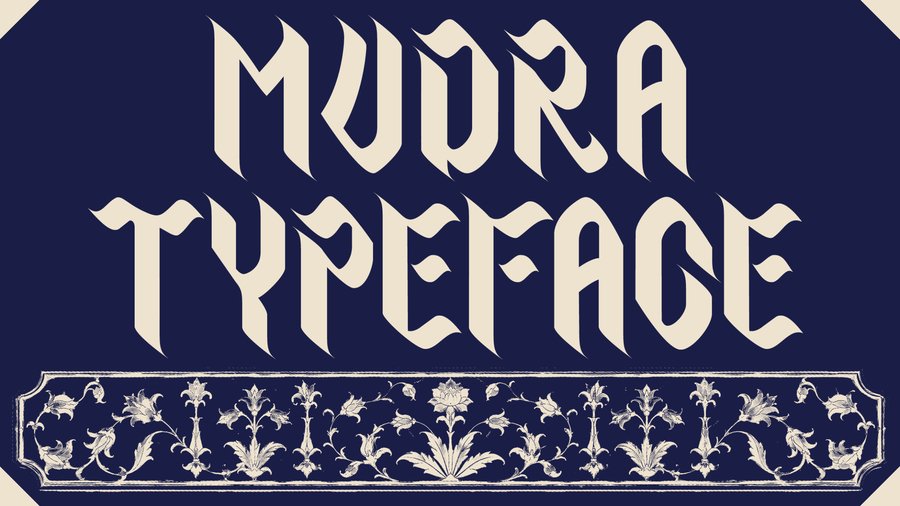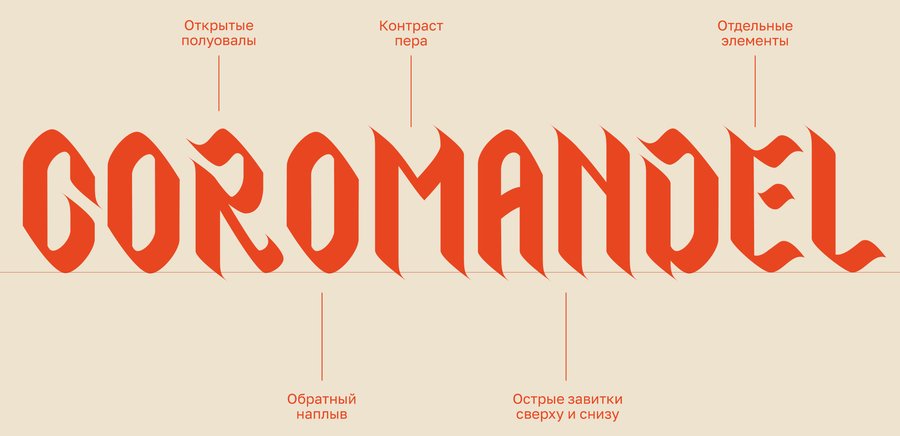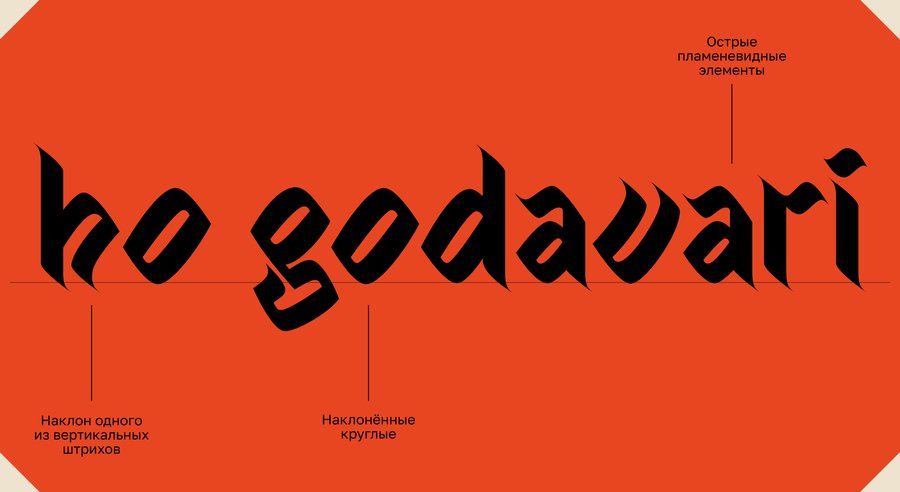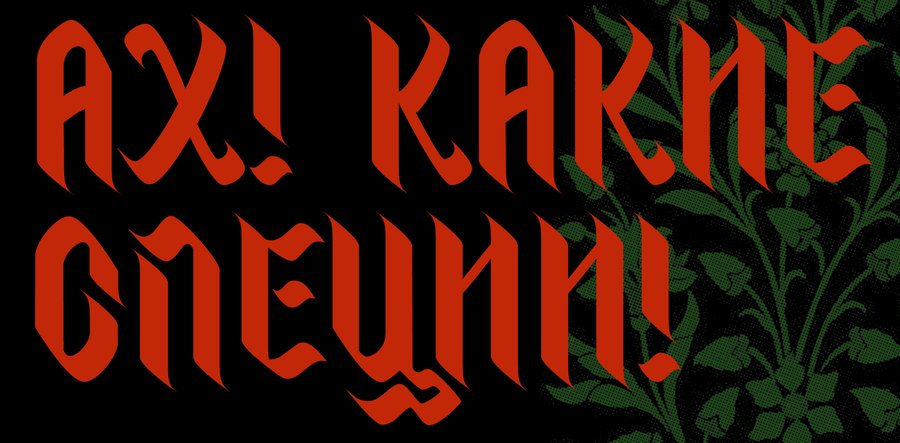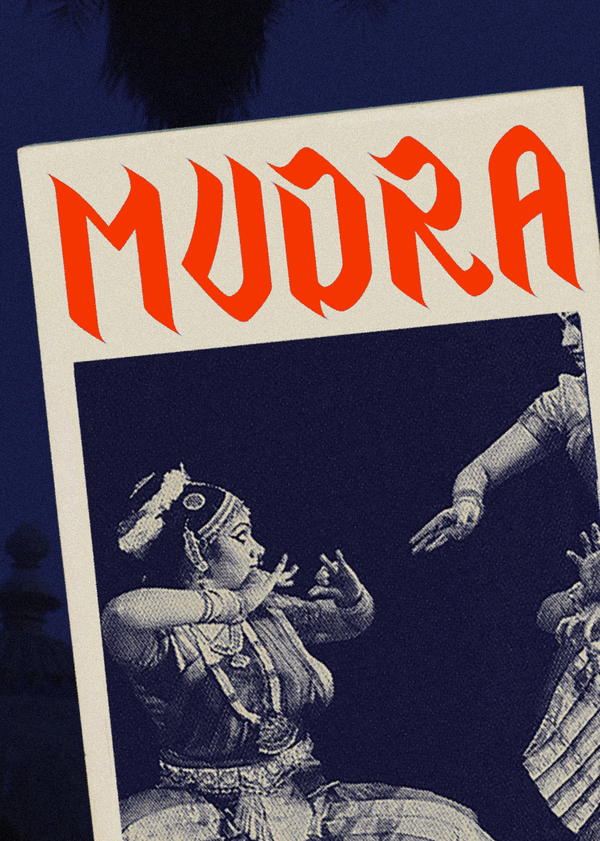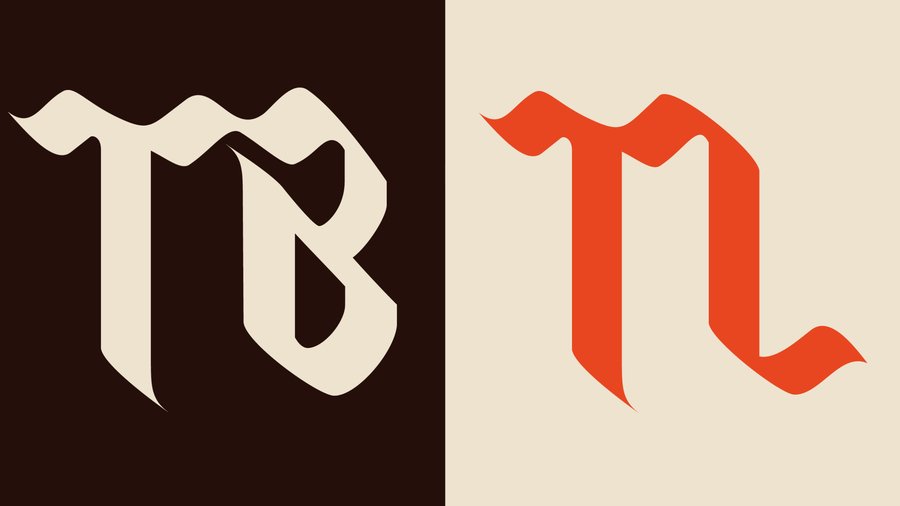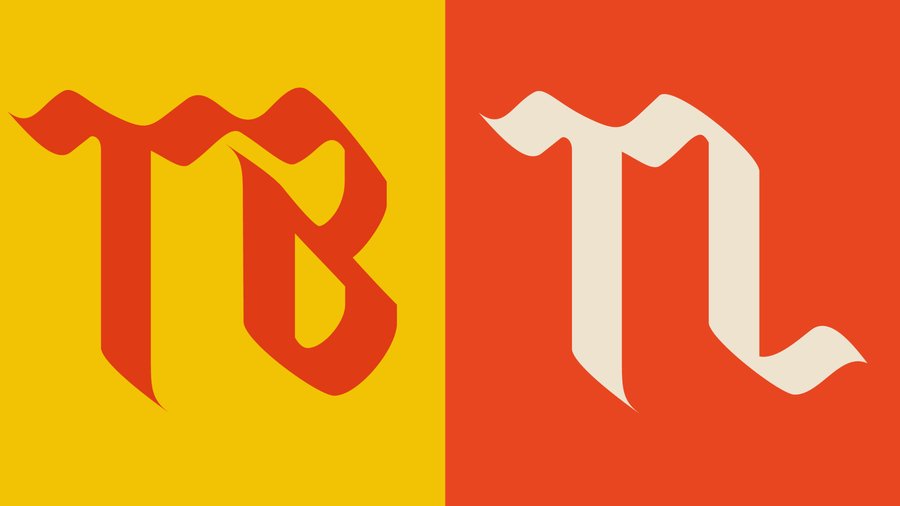
Mudra — акцидентный шрифт, основанный на индийской каллиграфической традиции. Его острый, пламеневидный рисунок вдохновлён пластикой надписей, выполненных кистью и найденных на улицах Нью-Дели
Мудра — санскритское слово, обозначающее символический жест руки в индийском танце, йоге и ритуале. Шрифт получил это название потому что, как и мудра, он построен на жесте — каллиграфическом движении пера, где форма буквы рождается из пластики руки